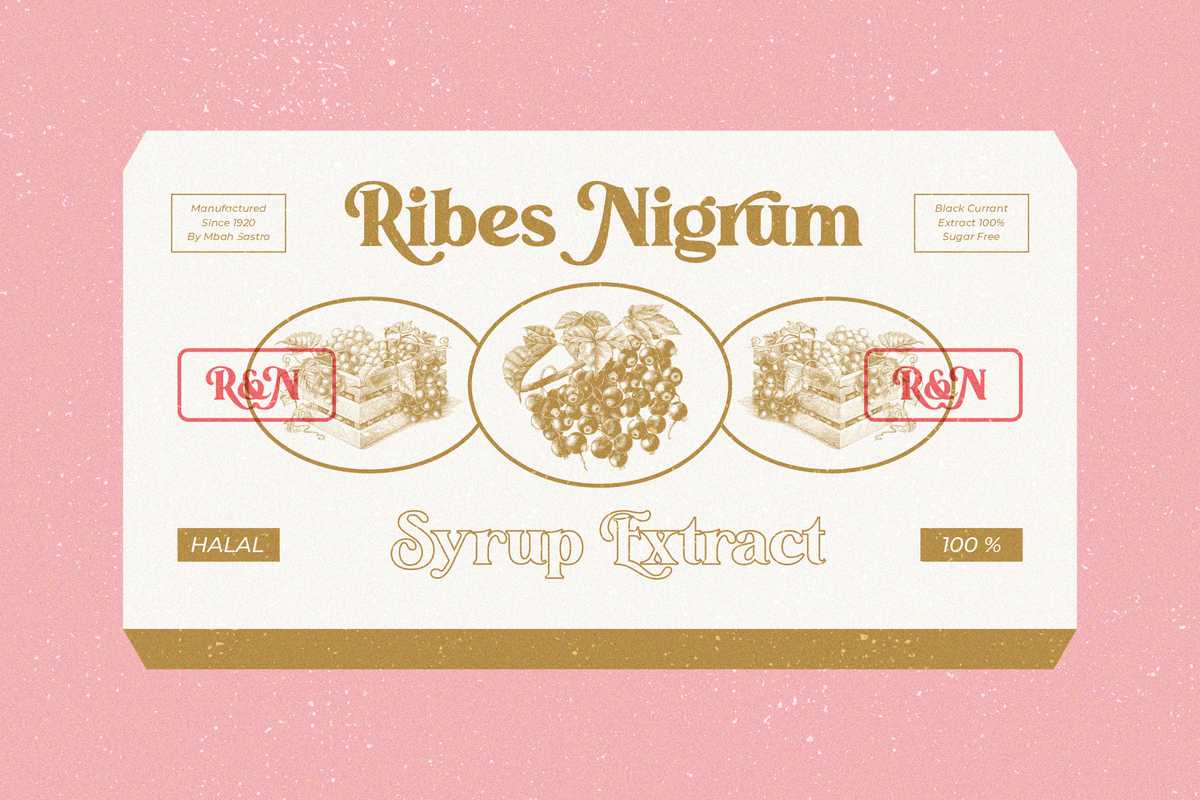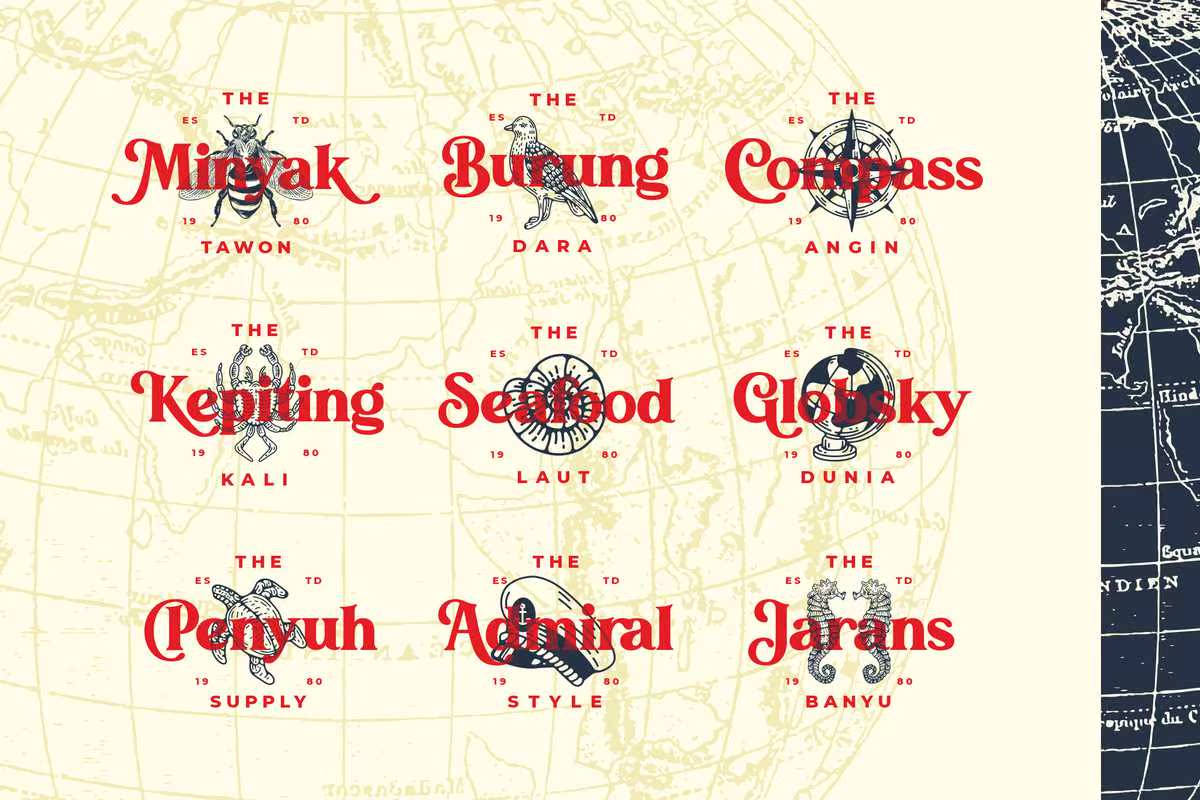
Alstoria是一种粗体显示serif字体。适用于您的项目品牌、包装、打印、标题和许多字体。包含320多个字形和10个连字。此字体还包含许多可选的清洗选项。适用于葡萄酒和模式样式,如Ouseeinor预览图像。Alstoria是一种粗体显示serif字体。适用于您的项目品牌、包装、,打印、页眉和多个字体。包含320多个字形和10个连字。此字体还包含许多可选的清洗选项。适用于葡萄酒和现代风格,如Ouseeinor预览图像。